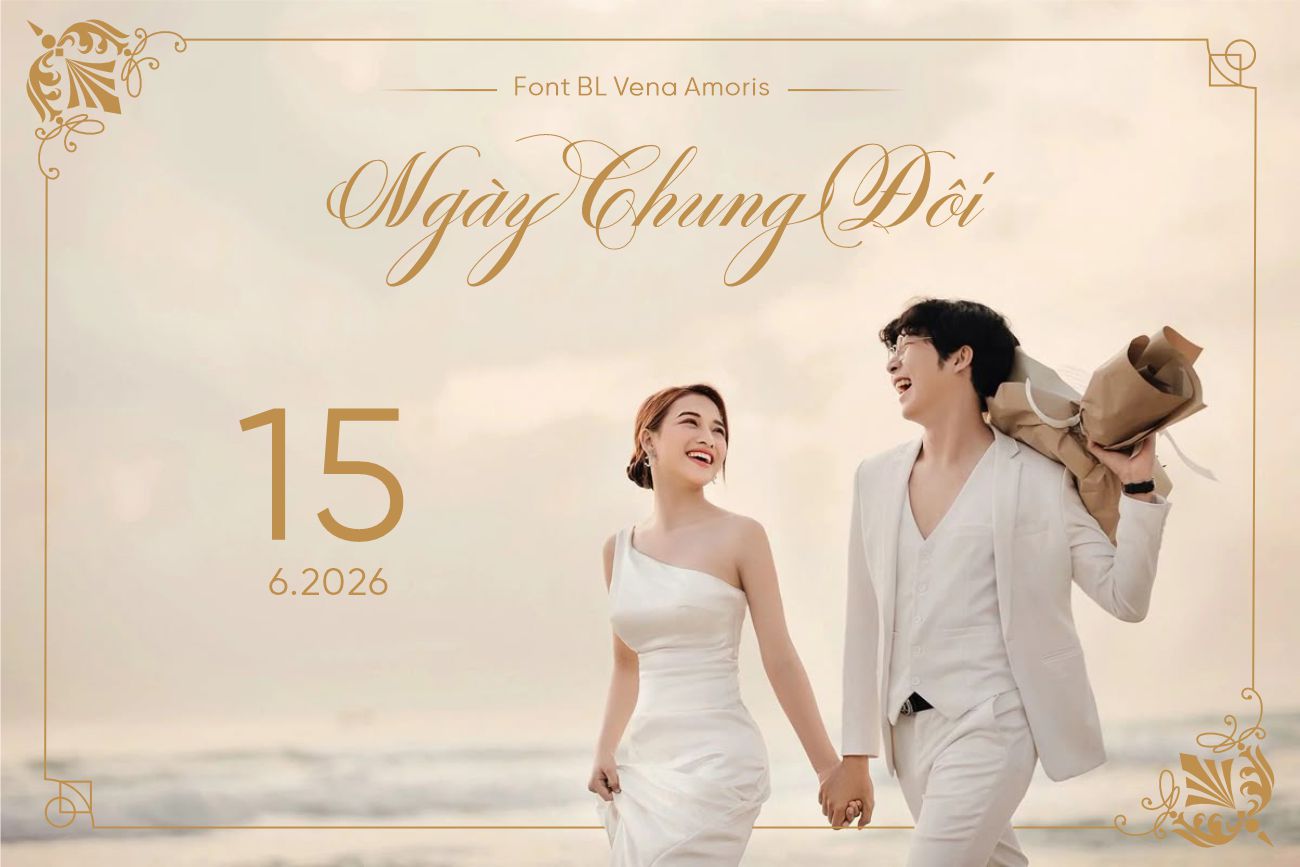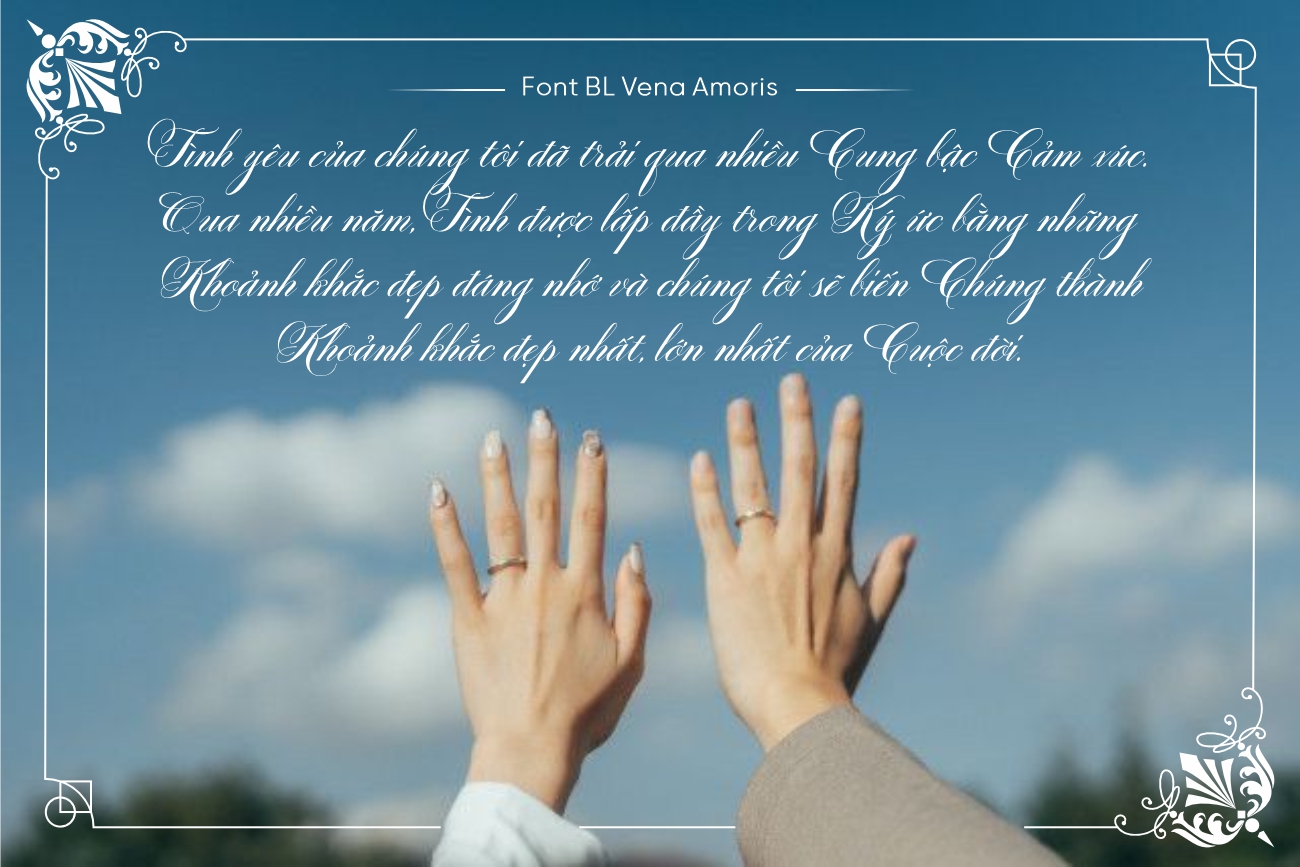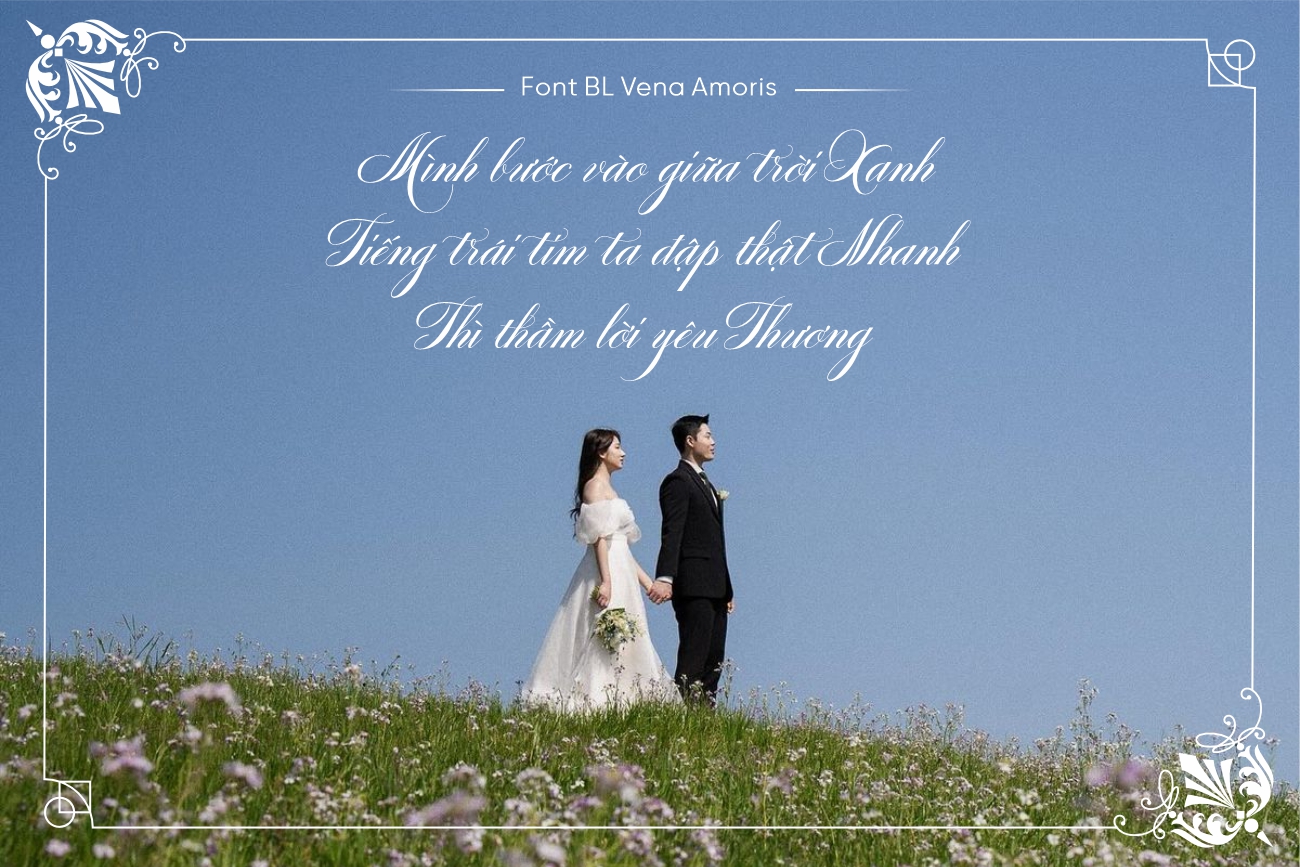
Font chữ handwriting BL Vena Amoris Việt hóa
Font chữ BL Vena Amoris là một kiểu script mang đậm hơi thở lãng mạn và cổ điển. Lấy cảm hứng từ thư tay thế kỷ 19, Vena Amoris tái hiện những đường nét viết tay mềm mại, uyển chuyển với các đường cong thanh mảnh và những nét bay bổng đầy tinh tế.
“Vena Amoris” trong tiếng Latin có nghĩa là “tĩnh mạch tình yêu”.
Đây là một khái niệm bắt nguồn từ thời La Mã cổ đại: người ta tin rằng có một mạch máu đặc biệt chạy thẳng từ ngón áp út bàn tay trái trực tiếp đến trái tim. Vì vậy, ngón áp út được xem là ngón tay dành cho nhẫn cưới hoặc nhẫn đính hôn, tượng trưng cho tình yêu vĩnh cửu và sự gắn kết trái tim.
Thực tế khoa học hiện đại cho thấy không có tĩnh mạch nào như vậy chạy thẳng từ ngón áp út đến tim. Tuy nhiên, niềm tin lãng mạn này đã trở hành truyền thống và được giữ lại trong nhiều nền văn hóa phương Tây, rồi lan rộng toàn cầu.
Đặc điểm nổi bật:
Phong cách copperplate script thanh lịch, uốn lượn tinh xảo.
Trang bị nhiều tính năng OpenType: ligatures, swashes, stylistic alternates… giúp chữ viết tự nhiên và đa dạng hơn.
Hỗ trợ nhiều ngôn ngữ Latin, phù hợp cho thiết kế toàn cầu.
Ứng dụng:
Vena Amoris đặc biệt thích hợp cho các thiết kế thiệp cưới, thiệp chúc mừng, logo cao cấp, bao bì mỹ phẩm – trang sức hay bất kỳ ấn phẩm nào cần một dấu ấn thanh lịch và lãng mạn.
Đây là một font chữ hoàn hảo nếu bạn muốn mang đến cảm giác sang trọng, tình yêu và sự gắn kết trong thiết kế.